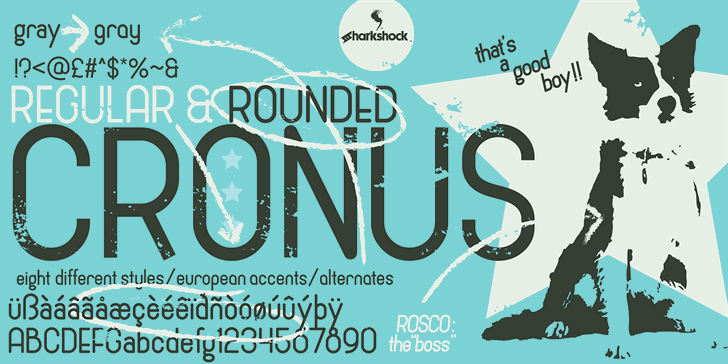
Cronus Font
A Cronus é uma fonte sans-serif desenvolvida por Hamilton para uso no formato OTF e TTF. Composta em sete variantes (Regular, Italic, Bold, Bold Italic, Rounded, Rounded Italic e Rounded Bold Italic), esta fonte foi criada pelo designer Dennis Ludlow em 2016. As licenças de todos os direitos reservados por Sharkshock podem ser encontradas no email fornecido. A Cronic é uma escolha ideal para aqueles buscando uma fonte clara e moderna, capaz de se adaptar tanto a aplicações digitais quanto gráficas. Suas linhas leves e arredondadas garantem um design limpo, enquanto o uso da variedade de estilos permite que você personalize sua mensagem para atender às suas necessidades de layout. Com uma paleta minimalista e fácil de ler, a Cronic pode ser usada em diversos contextos, desde sites profissionais até materiais gráficos publicitários. Esta fonte é perfeita para quem busca trazer elegância ao seu design digital sem comprometer a legibilidade.